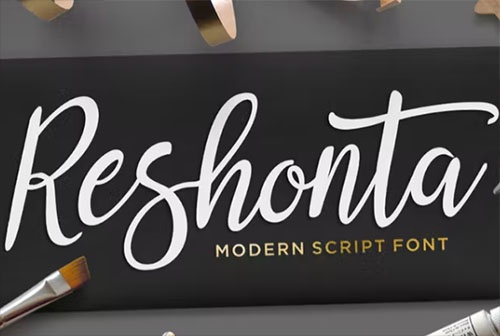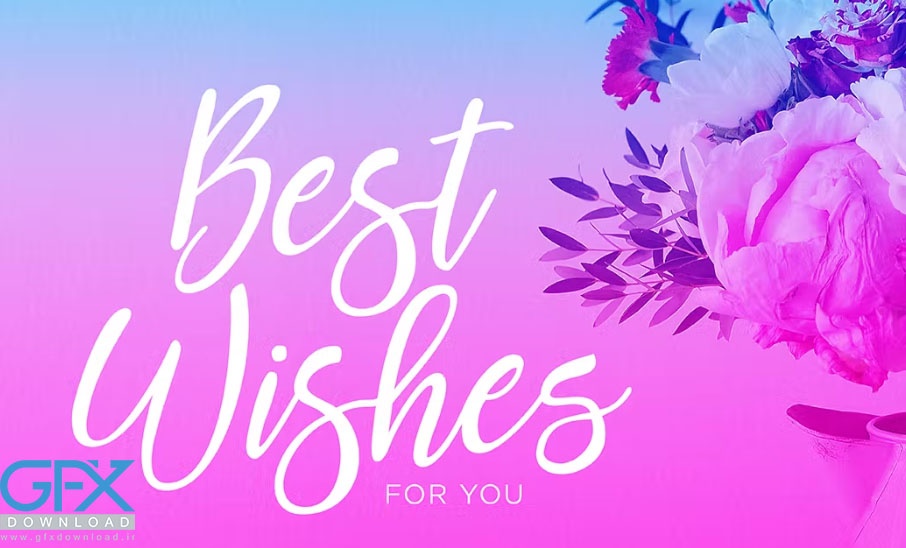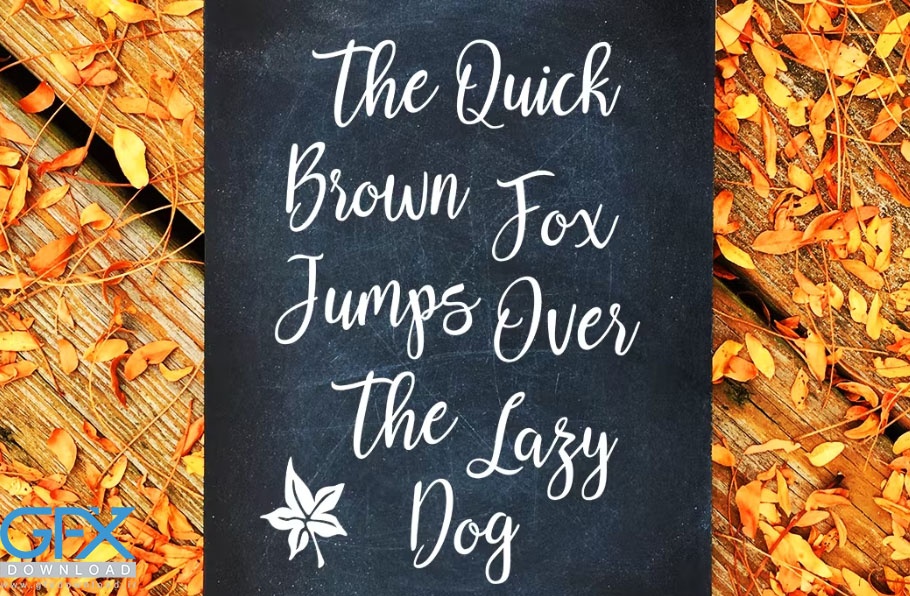
یک فونت خط مدرن خوشنویسی است که با قلم و براش ایجاد شده است. رقص خط پایه با حروف کوچک جایگزین. روی کاغذ نقاشی شدند. اسکریپت Reshonta شامل چندین لیگاتور، جایگزین و پشتیبانی بینالمللی برای اکثر زبانهای غربی است. برای فعال کردن کاراکتر جایگزین، به برنامه ای نیاز دارید که از ویژگی های OpenType مانند Adobe Illustrator CS، Adobe Indesign و CorelDraw X6-X7، Microsoft Word 2010 یا نسخه های جدیدتر پشتیبانی کند. برای دانلود فونت انگلیسی خوشنویسی Reshonta Script از جی اف ایکس دانلود به ادامه مطلب مراجعه کنید.
این فونت جذاب ایده آل برای لوگو، دعوت نامه عروسی، کارت ویزیت، پوستر، کالا، کارت تبریک، چاپ، بنر وبلاگ، پوشاک، نقل قول و موارد دیگر می باشد.